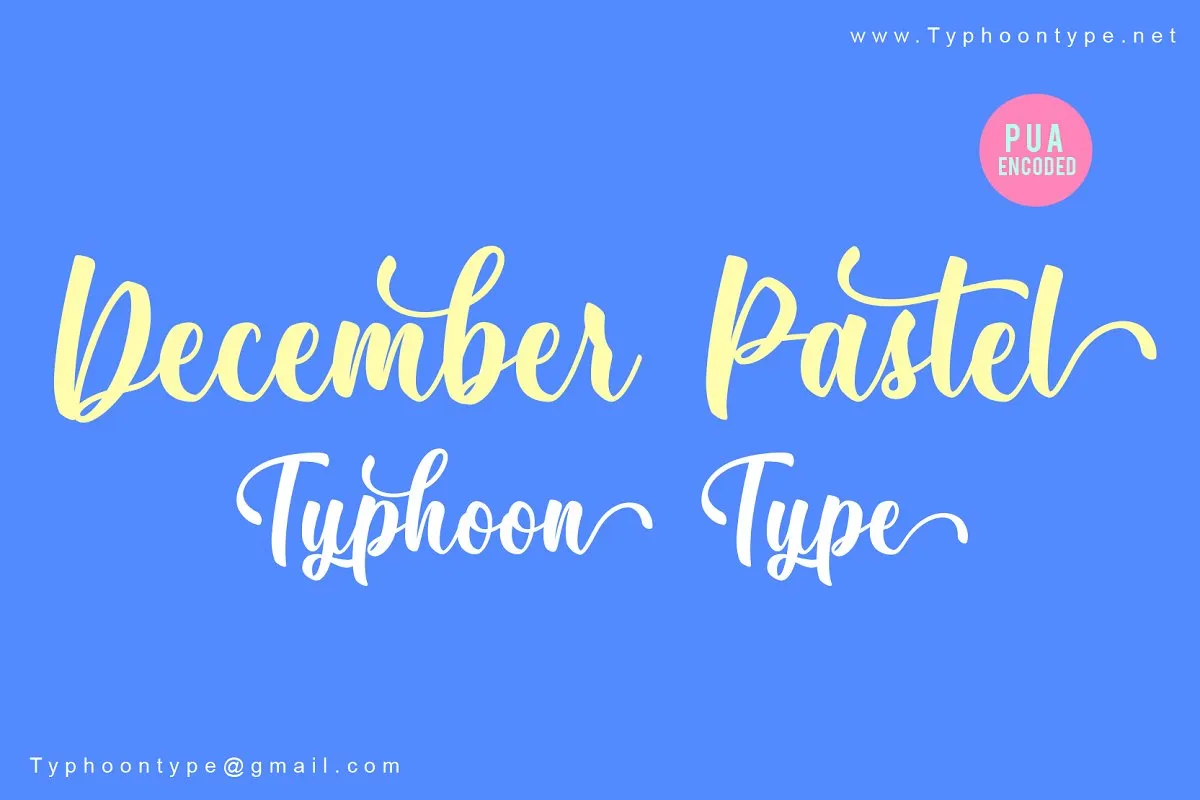
Olá! Introduzimos a Fonte Dezembro Pastel (December Pastel Font), uma elegante fonte de script dedicada aos amantes do estilo retrô e da moda moderna. Este fonte é perfeito para projetos gráficos, especialmente se você está procurando por algo que transmita harmonia tipográfica em sua arte digital. December Pastel Script oferece um toque de sofisticação e elegância para qualquer projeto, seja ele uma camiseta, etiquetas personalizadas, cartões de aniversário ou até mesmo logotipos exclusivos. Esta fonte é perfeitamente adequada para a necessidade de design gráfico, sendo ideal tanto para o ambiente digital quanto o físico. O designer 0001themes criou um design cuidadoso e delicado que combina perfeitamente com a estética de muitas campanhas de marketing, logotipos e materiais promocionais, como etiquetas de produtos, embalagens, e até mesmo o conteúdo das redes sociais. December Pastel Font é uma escolha inteligente para aqueles que buscam um toque sofisticado em seus designs enquanto manter a sua personalidade única.